Verso Milan-Frosinone: ecco i font della nuova maglia
Nella partita di domani sera a San Siro con il Frosinone sarà presentata la nuova maglia del Milan per la stagione 2019-2020. Nei font si torna al vintage
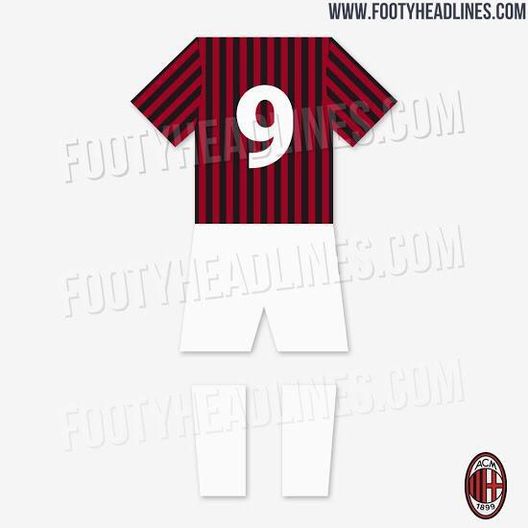
"ULTIME MILAN - Milan - Frosinone, di scena domani alle 18.00 a San Siro, sarà anche l'occasione per ammirare la nuova maglia ufficiale per la stagione 2019-2020.
Il nuovo font della divisa ufficiale 2019-2020
"Nel sito specializzato FootyHeadlines.com si può notare anche l'utilizzo del font per i numeri (nella foto) che richiama molto lo stile vintage. Nell'eventualità della qualificazione in Champions League sarebbe questo lo scenario in panchina: continua a leggere >>>